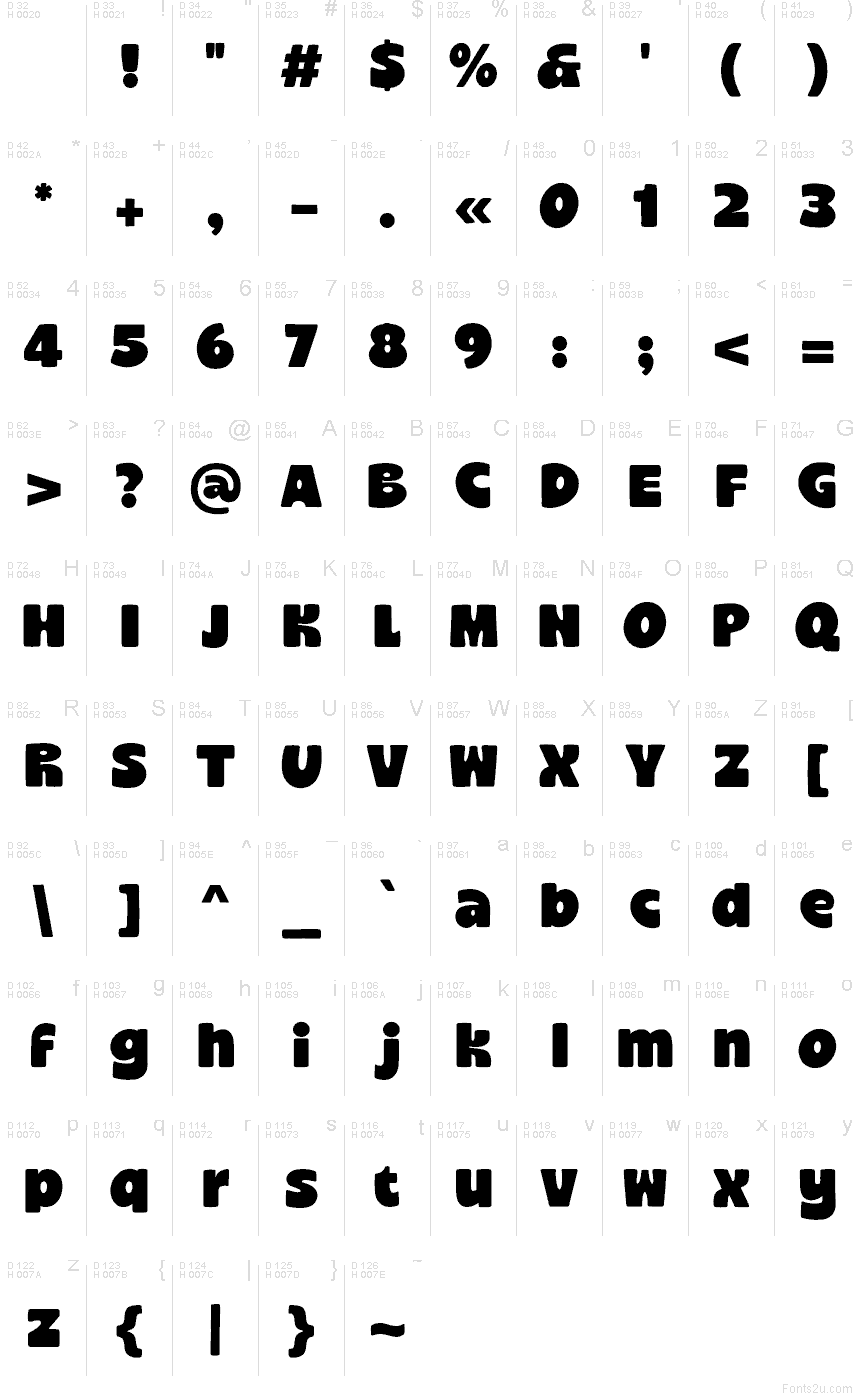
Faster Break de Namara Creative es una tipografía display gratuita de estilo desenfadado, con letras anchas y redondeadas y un trazo dinámico hecho a mano. Sus curvas irregulares y el grosor sutilmente variable de sus trazos evocan la lúdica rotulación de los años 70. Las formas se sienten suaves, contundentes y con un contorno agradablemente irregular.
Su toque de dibujos animados retro la hace ideal para carteles musicales y gráficos de festivales. También aporta un tono relajado a los envases de aperitivos. Asimismo, se adaptan a libros infantiles y a merchandising alegre.
Faster Break es una tipografía display gruesa.
- Formas de letras tipo burbuja redondeadas
- Caracteres estándar y puntuación
- Alternativas, ligaturas, swashes y soporte multilingüe